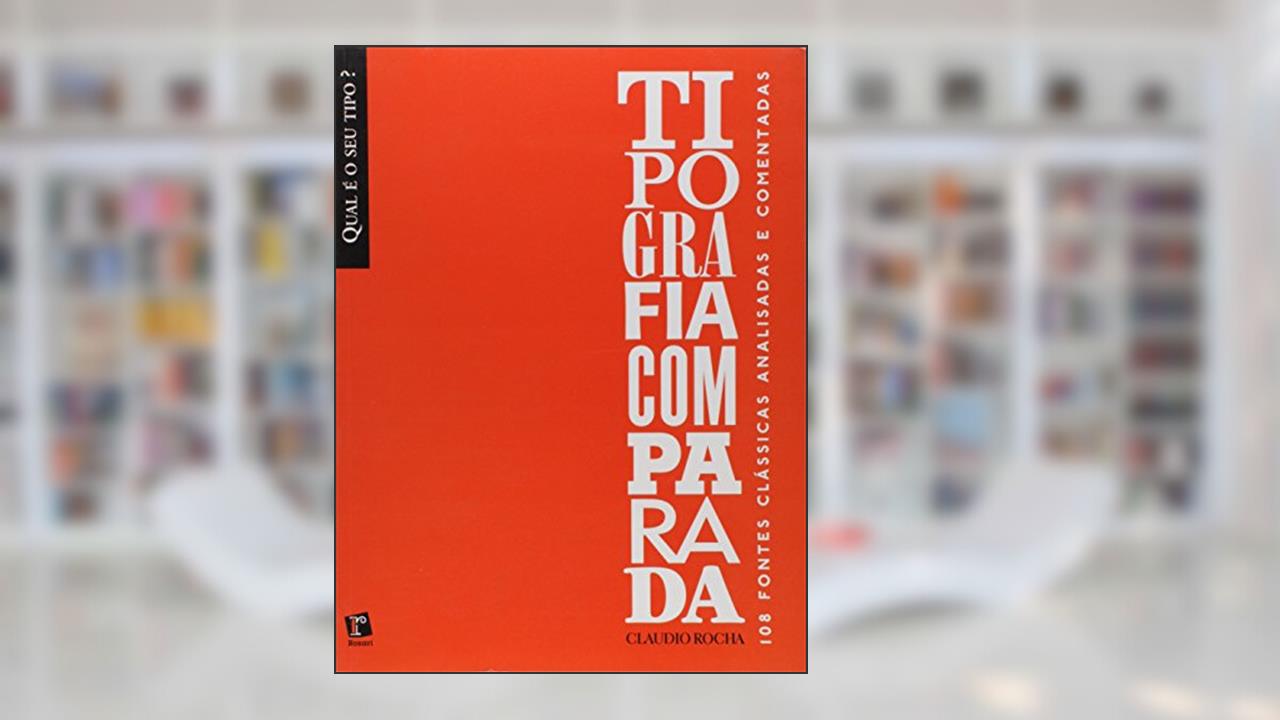
Tipografia Comparada - 108 Fontes Clássicas Analisadas e Comentadas, do autor Claudio Rocha
Tipografia Comparada - 108 Fontes Clássicas Analisadas e Comentadas
Claudio Rocha
Tipografia Comparada - 108 Fontes Clássicas Analisadas e Comentadas é muito mais do que um simples compêndio sobre fontes. Esta obra é um mergulho vigoroso na alma do design gráfico, um manifesto visual que explora a ressonância das letras, seu impacto na comunicação e a magia que elas podem evocar. Claudio Rocha, com maestria e eloquência, nos guia por um labirinto de 108 fontes clássicas, cada uma delas carregada de significados, histórias e emoções, como se cada tipografia fosse um personagem à espera de ser desvendado.
Neste universo tipográfico, você não se depara apenas com tipos de letra; você é confrontado com a essência do design. É como se cada fonte estivesse contando uma história que foge do papel e se insinua na sua mente. Aqui, as curvas e retas se transformam em argumentos, sutilezas e sentimentos. As análises de Rocha são tocantes e profundas, revelando não só a técnica, mas a intenção por trás de cada traço. Desde o clássico Garamond até a ousada Helvetica, cada fonte ganha vida e evocação, tornando-se parte de uma conversa que desafia o leitor a enxergar além do que está impresso.
Os comentários de leitores sobre a obra são variados e intensos. Muitos se encantam pela profundidade das análises, descrevendo como as discussões sobre cada fonte os levaram a repensar não apenas suas escolhas tipográficas, mas também a maneira como percebem o conteúdo visual ao seu redor. Por outro lado, alguns críticos apontam que o livro pode ser denso para iniciantes, exigindo um apreço prévio pelo design, mas para os apaixonados pela tipografia, isso é um convite a um banquete sem igual.
A importância dessa obra transcende a mera análise técnica; ela é uma reflexão sobre nossa relação com o design e a forma como ele molda nossas interações no dia a dia. Em um mundo saturado de comunicação, a tipografia não é apenas um detalhe estético, mas um poderoso veículo de mensagem. Ao ler Tipografia Comparada, você se permite questionar o que está por trás de cada letra que lê, compreendendo que cada escolha tipográfica carrega consigo uma carga emocional que pode influenciar a percepção e a reação.
O contexto histórico em que Rocha escreve também é relevante. Publicado em 2003, o livro surge como uma resposta à crescente necessidade de comunicação visual clara e impactante em uma sociedade cada vez mais digital. As fontes clássicas analisadas neste livro não são apenas vestígios do passado, mas inspirações para um presente que demanda cada vez mais atenção aos detalhes.
A tipografia tem o poder de transformar a forma como a mensagem é recebida. Cada letra, cada espaço, cada linha - tudo se conecta emocionalmente. Você não apenas lê as palavras; você sente cada uma delas. E isso é o verdadeiro poder de Tipografia Comparada: um chamado insuspeitado para que todos nós, designers e leigos, revisitemos o universo da comunicação escrita com novos olhos, prontos para decifrar narrativas que vão muito além do óbvio.